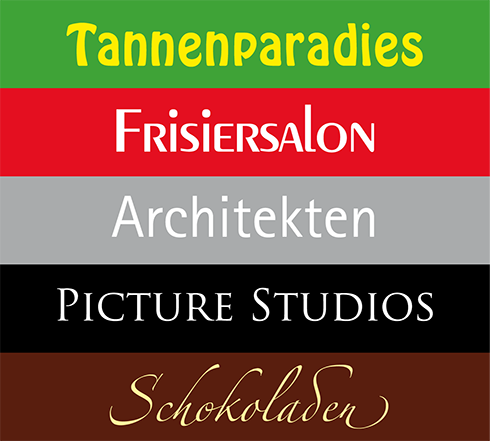
Es gibt Berufszweige, die gerne auf die immer gleiche Schrift zurückgreifen – nicht nur in Deutschland. Die Lieblingsschrift der Tannenbaumverkäufer in den vorweihnachtlich geschmückten Städten ist sicherlich Hobo. Ein Klassiker bei den Frisören ist seit Jahren Peignot. Mitte der 90er Jahre entdeckten die Architekten die Rotis als ihre Schrift. Die Schriftenexperten dieser Welt gähnen über die (typografische) Einfallslosigkeit Hollywoods – Trajan auf über 50 % aller Plakate. Aufsteiger des Jahrzehnts beim Verpackungsdesign ist Zapfino, vor allem bei süßen Säften und bitteren Schokoladen. Wer kennt weitere Branchen, denen es an typografischem Einfallsreichtum mangelt? Bitte Kommentar mit Bild …
Traditionell-ungarische Restaurants: Arnold Böcklin, siehe http://twitpic.com/i60sw und http://twitpic.com/iabfw.
Stimmt, wobei ich Architektur(büros etc.) immer auch mit Futura verbinde:
Die Rotis ist ganz klar auch ein Fall für alles Medizinische (leider ohne Bild).
Eras für Copyshops, Plott-Dienstleister und selbsternannte Wald-und-Wiesen-”Werbeagenturen” ;)
ich sag nur asia-laden und asia-bistro
Mode: Didot & Futura (Majuskeln)
Optima, die schrift mit gürtel und hosenträger gleichzeitig, für alle kosmetik verpackungen.
@ anita:
asia-laden & asia-bistro zeichnen sich nach meiner beobachtung aber gerne durch freihand-klebefolienausschneiden-isolierband-gaffa-tape-buchstaben-typographie aus…
Galerien greifen gern auf die Avantgarde zurück, was wohl eher am Namen als an der typografischen Qualität liegt. Die Scala wiederum wird von verdammt vielen Theatern verwendet. In München war das die Hauschrift des Prinzregententheaters. Als die auf Eurostile wechselten (neuer Intendant, alte Sünden), griff die Bayerische Staatsoper (Fons Hickmann) zu. Sicher hat hier auch der Schriftname bei der Präsentation geholfen. Also Schriftentwerfer, sucht euch gute Schriftnamen aus, die bei einer großen Zielgruppe punkten! Visions oder Weltkulturerbe sind sicher gute Namen :D
Öko findet Officina immer Metageil.
Hobo sieht eher aus wie Palmenparadies
Viele Frittenbuden,Copyshops, Selbermacher und Geburtstagseinladungdrucker kennen nur die Eine. Die Unsägliche.
Och, es hat immerhin 12 Einträge gebraucht, bis DAS wieder kommt.
Ich finde eigentlich, dass diese Branchen eher den Hang dazu haben auch mal Schriften zu benutzen, die man noch nicht tausendmal gesehen hat. Das geht zwar öfters in die Hose, aber grad auf Weihnachtsmärkten kann man einiges an sehr hübschen Ideen entdecken. Natürlich nur, wenn man sich nicht die ganze Zeit über die Comic-Sans-, Hobo-, Arial-, Zapfino-, usw.-usf.-Schilder aufregt.
Also besser Augen auf nach was Neuem anstatt immer nur die bekannten Sachen wiederfinden! ;)
Das mit der Rotis ist bei den Architekten aber eine ganze Weile vorbei, zumindest seit Foster sie nicht mehr benutzt… und entsprechend den britischen Vorbildern ist es derzeit oft etwas in Richtung Univers/Helvetica, wobei farblich in Deutschland grau und weiß dominieren.
Die Bäcker nehmen alle Cooper Black… Noch nie aufgefallen?
Das mit der Rotis bei Architekten kann ich überhaupt nicht bestätigen. Dafür, dass Architekten ja auch Gestalter sind, herrscht unter diesen vielmehr eine erschreckende Typografie-Ignoranz. Sehr viele kennen die Rotis wahrscheinlich nicht einmal. Oder den Unterschied zw. Arial und Helvetica.
Man kann ja von der Rotis halten, was man will, aber der Otl hatte wenigstens eine Haltung. Die Futura auf seine Visitenkarte drucken, weil die Schrift im Architektur-Coffeetablebook doch auch so chic aussah, zeugt hingegen nicht von Haltung.
Die Kabel für Waschsalons. Achtet mal drauf.
Speditionen schmücken sich des öfteren mit der Revue.
Wie heisst denn bloß diese Schrift, die für viele so „griechisch“ ist, ihr wisst schon: Restaurant Athen… bei euch um die Ecke?
gern genommen auch die VAG Rounded für Waschsalons
@ Christina
Das ist die Lithos.
Arial und Verdana sind mittlerweile auch schon überall.
Rechtsanwälte in der Schweiz lieben offensichtlich Verdana … :(
geizkragen lieben die verdana. dafür braucht man nichtmal eine ausbildung, das ist mein einfach …
Ikea liebt die Verdana und hat sie gleich mal zur neuen Hausschrift gemacht … traurig.
Aber wo bleiben die Bilder?
Viele Copyshops/Internetcafes scheinen die Bauhaus 93 sehr zu mögen.
@ Roman.
Klar, die Rotis ist umstritten (bei mir die Semiserif, die mag ich ü-ber-haupt nicht), und man mag wirklich von ihr halten, was man will, aber:
Die Serif ist meines Erachtens eine der besten Buchsatzschriften überhaupt. Vor ein paar Monaten las ich eines in der Semiserif gesetzt und beim Lesen merkte man schon, wie klar und angenehm das Auge auf den Zeilen ruhte. Erst spät fiel mir auf: »Verdammt! Das ist ja Rotis!«
Wunderbar. :-)
@kumi: Sogar Otls „Die Welt als Entwurf“ lässt sich nach kurzer Gewöhnungsphase sehr angenehm lesen, „trotz“ sans-serif und konsequenter Kleinschreibung.
@HD Schellnack: Die Rotis bei Foster + Parters auszutauschen war eine folgerichtige Entscheidung. Nachdem Sir Foster mit Otl Aicher sicherlich gut beraten und befreundet war, waren nach einigen Jahren dem Marktführer derartig viele Büros in dessen Schriftwahl gefolgt, dass es konsequent war, einen typografischen Weg einzuschlagen, der weitaus weniger unaufwendig zu imitiert ist. In sämtlichen möglichen Anwendungen des Erscheinungsbildes — von Briefbögen über Visitenkarten, von CD-Hüllen über die Beschilderung bis zu Adressaufklebern – ist die Logotype eine reflektierende silberne Heißfolienprägung und hat damit eine materielle Opulenz, die andernorts sicherlich bei Verbrauchsmaterialien als verschwenderisch angesehen wäre.
Zunächst kam die eingesetzte Schrift Akzidenz Grotesk im 2000 von Prestel verlegten Buch ›On Foster … Foster on‹ zum Einsatz. Erst später übertrug sie Thomas Manss & Company auf das gesamte Erscheinungsbild des Unternehmens sowie alle folgenden Bücher und auch Magazine.
Die Zapfino erfreut sich, neben ihrer ‘Schwäche’ für Süßkram, auch bei Weinstuben, -gütern und Weinfest-Einladungen (zu) großer Beliebtheit.
An Zapfino ist wohl Apple schuld, die die Schrift seit 2001 als Standard-Font unter Mac-OS X mitliefern.